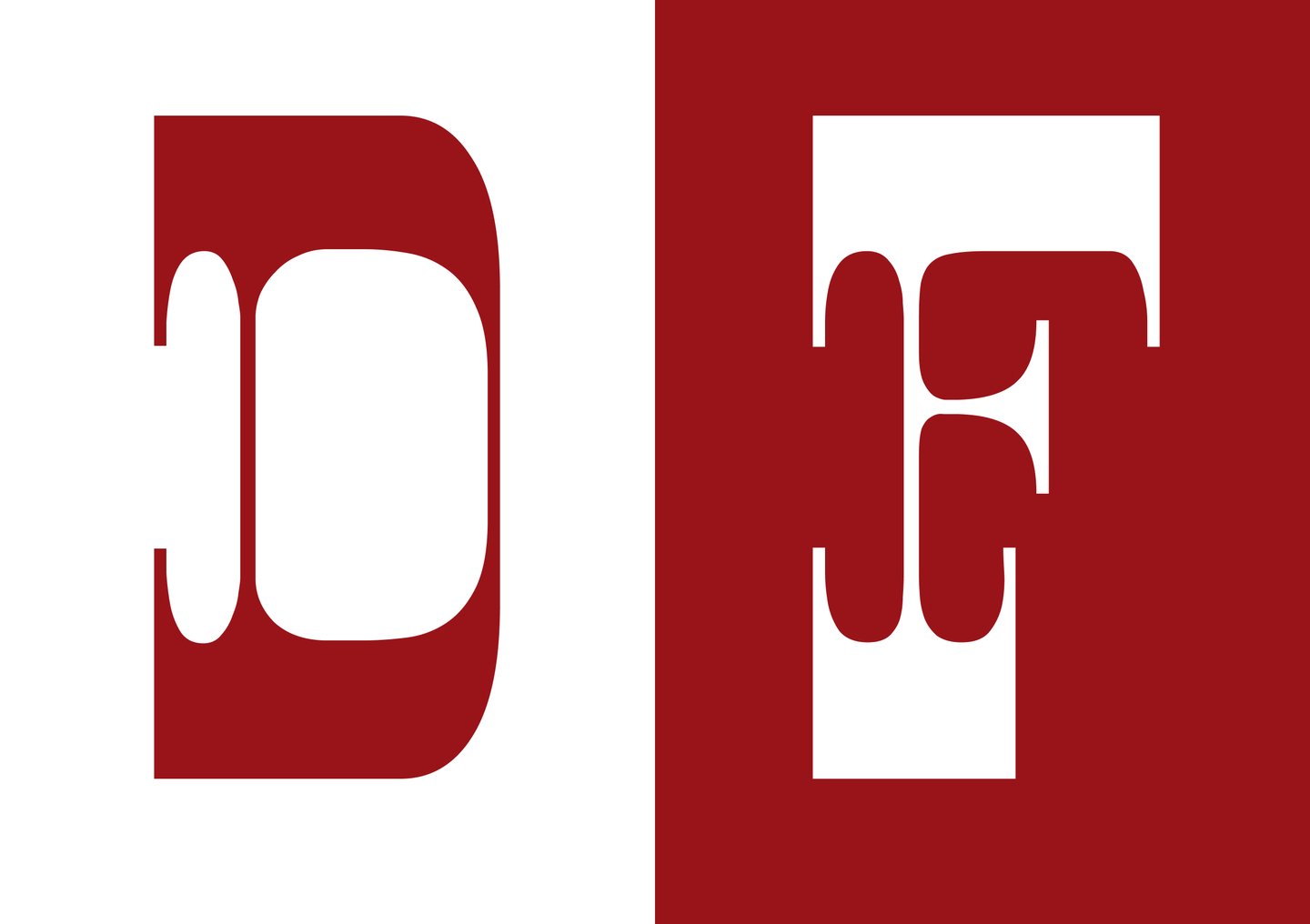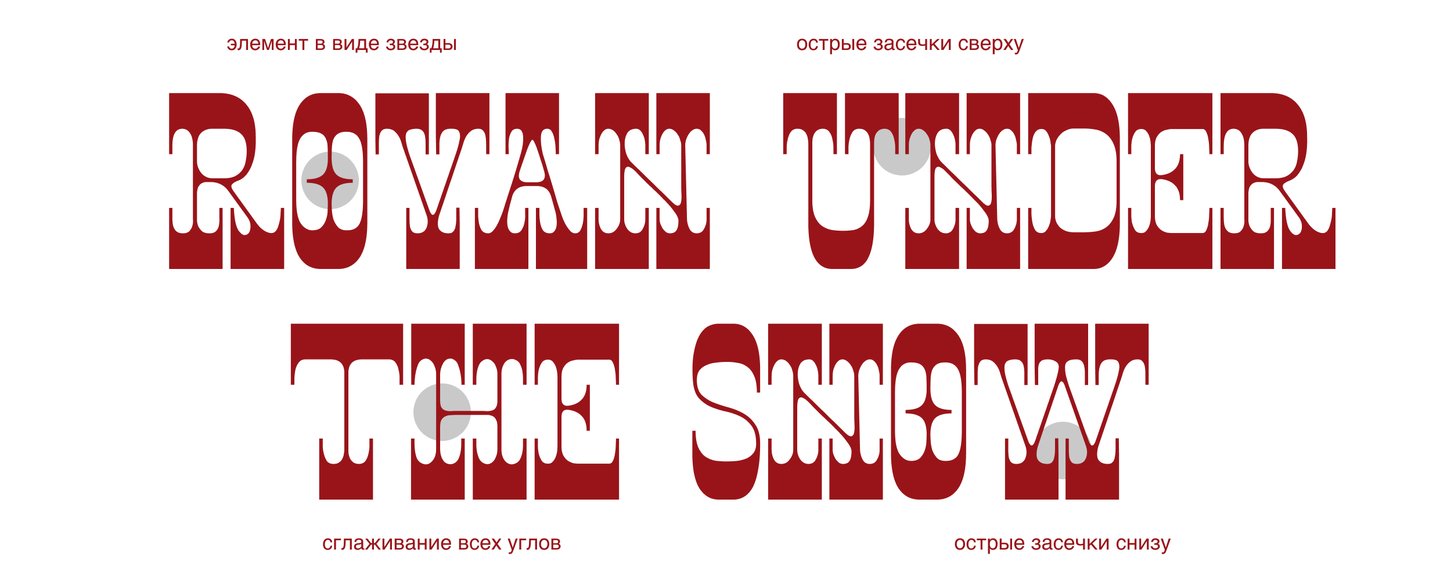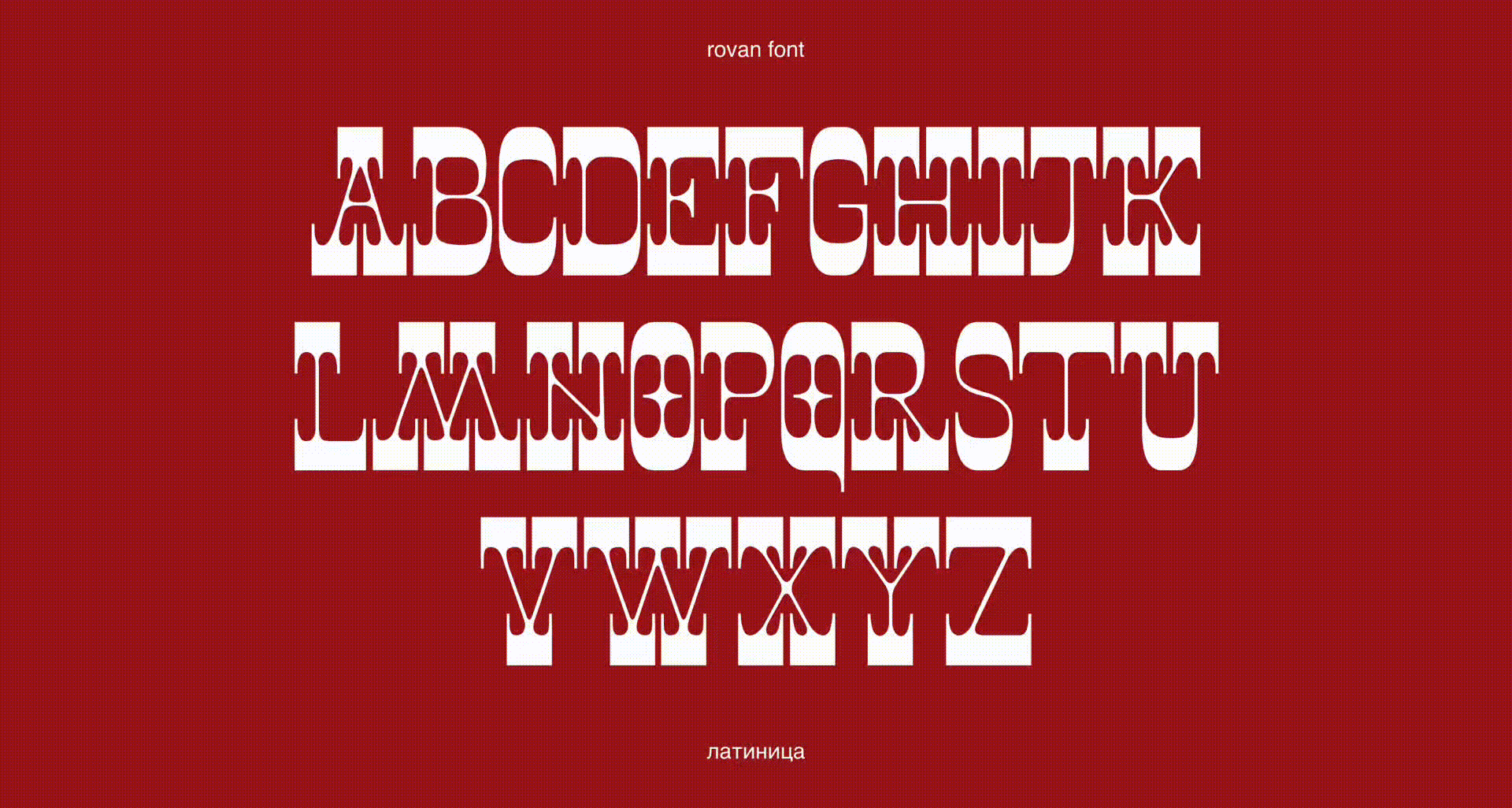
Rovan — это акцидентный шрифт, вдохновленный итальянскими шрифтами. Основная особенность — острые засечки. Благодаря им и элементу в виде звезды шрифт создает немного мрачное и волшебное настроение.